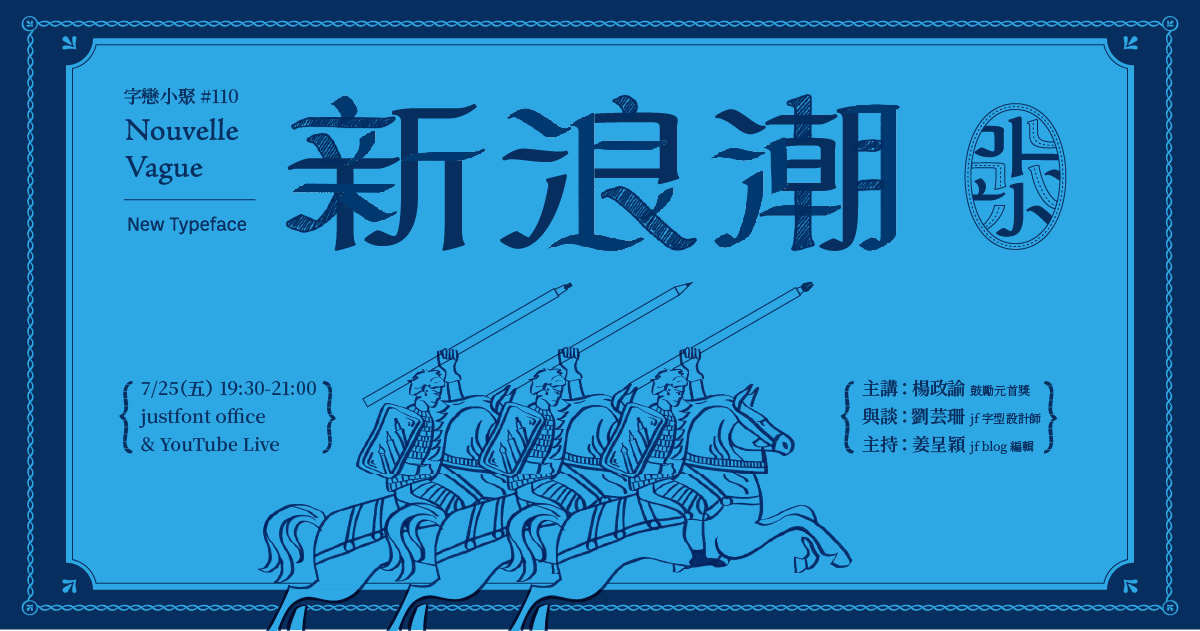
將拉丁書寫造形, 結合漢字創作, 會長成什麼樣子?
這是造字鼓勵元第八屆首獎得主楊政諭的創作動機。透過跨文化、跨語種的設計實驗,政諭爬梳歐文歷史,以平頭筆書寫漢字,反覆實驗,製作名為「新浪潮」的字體提案。
一年過去,從筆型拼貼,到融合東西書寫風格,政諭透過比例結構、書寫工具、筆韻到寫法,種種細節來實踐造形融合與數位化的進程。
歐文書法的漢字設計並不少見,政諭的實驗是老調重彈,還是全新的眼光? 來聽聽政諭以及輔導老師芸珊的分享。
🖋️ 歐文書法是什麼?
🖋️ 結合漢字的方法百百種,但是⋯⋯!
🖋️ 更精緻的細節設計!
🖋️ 新浪潮的下一步?
楊政諭
雲林科技大學視覺傳達設計系碩士生。大學畢業後進入設計領域工作數年後,重回校園鑽研字體創作。新浪潮同時也是他的碩士論文。